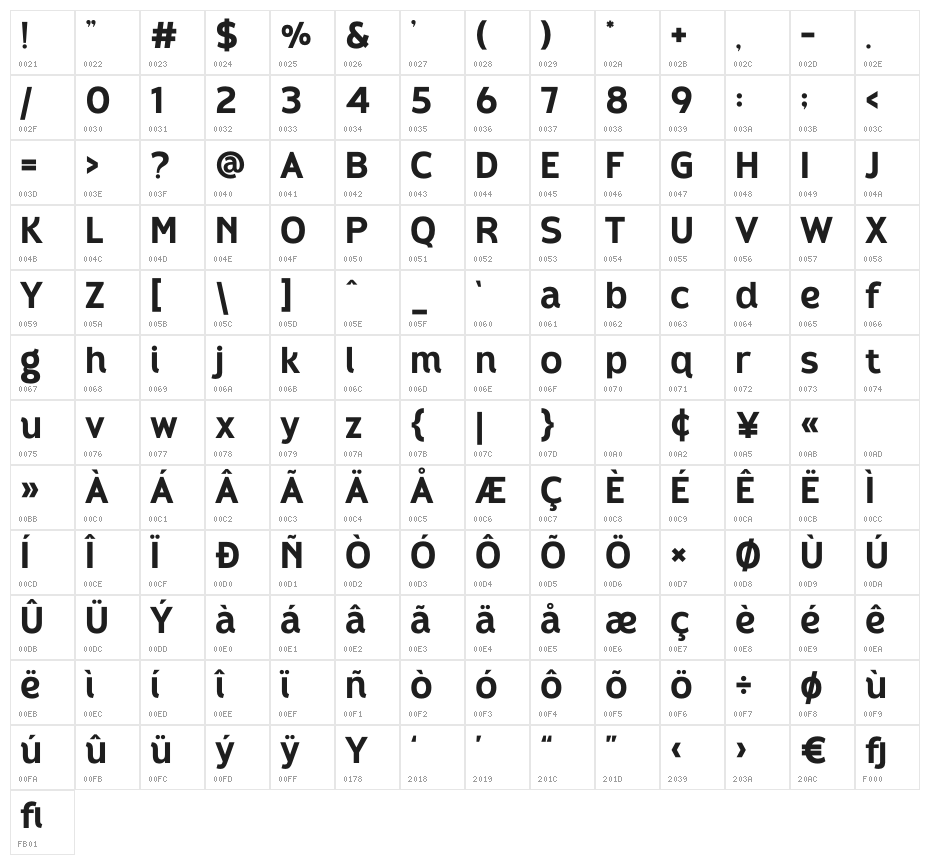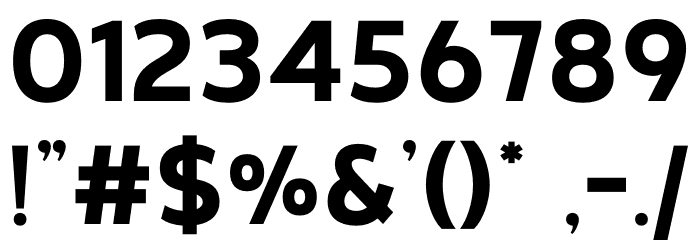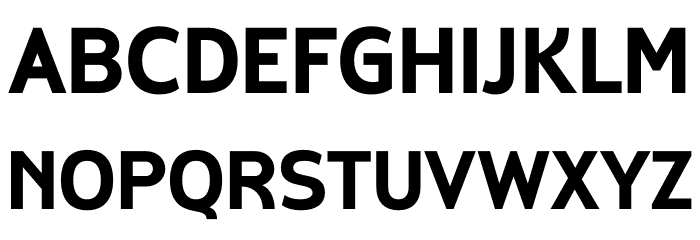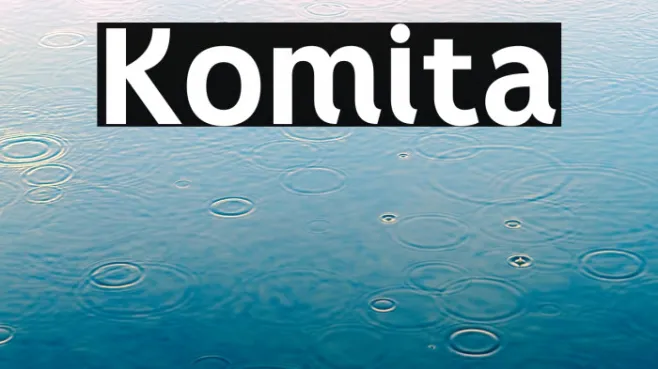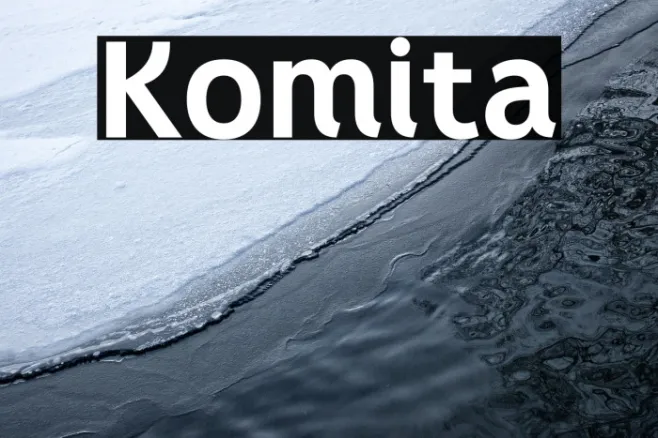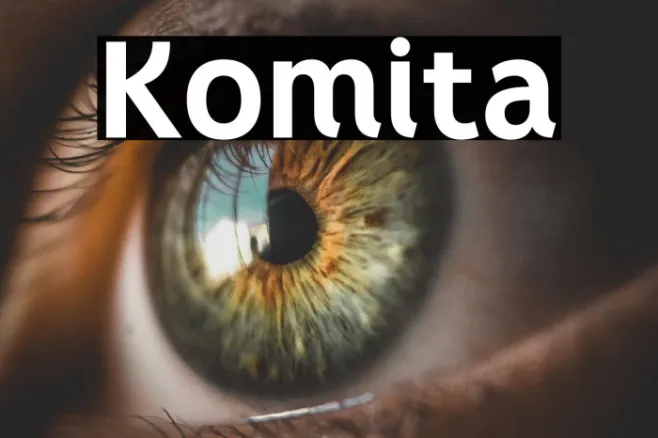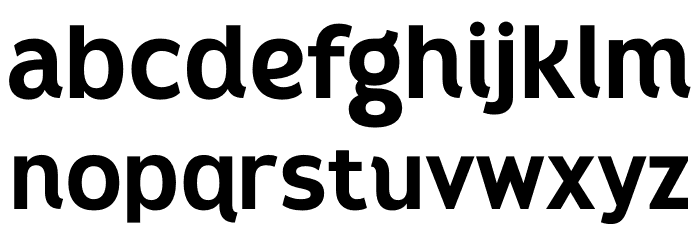
Komita Font
| Schriften Familie | Komita |
| Kategorien | Sans Serif |
| Anwendungsfall | Headlines, Logos, Web design |
| Vorgeschlagene Projekte | Ideal for branding, advertising, web design, and editorial layouts due to its clarity and modern appeal. |